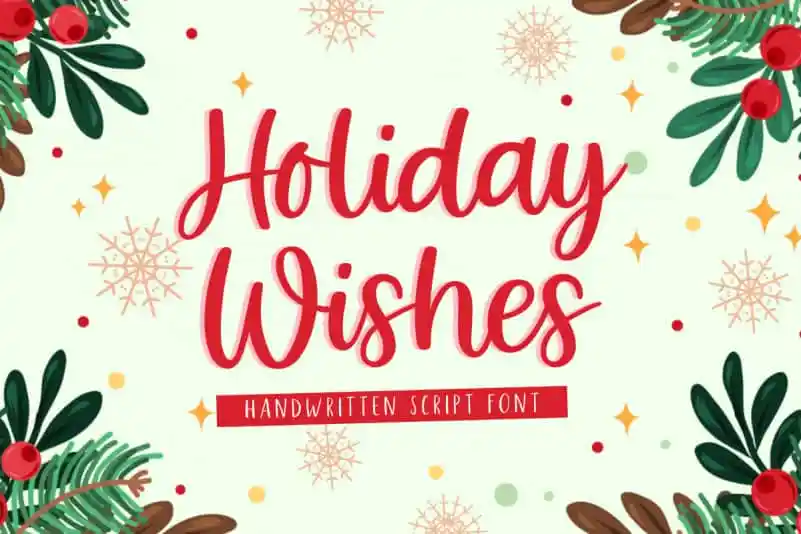
Holiday Wishes Script Font – Fonte Grátis
Holiday Wishes Script Font
A fonte ‘Holiday Wishes Script Font’ é uma elegante tipografia escrita à mão que adicionará um toque fresco e moderno a seus designs digitais. Com seu caráter natural e fluido, esta fonte será perfeita para estilos de branding, design digital, redes sociais, websites, blogs, cartões de business, Instagram, convites, logotipos e até mesmo criações personalizadas no Cricut. Suas linhas suaves e características únicas garantem que sua identidade visual seja única, se destacando em qualquer plataforma ou aplicação digital onde ela for usada. A ‘Holiday Wishes Script Font’ é uma ótima opção para quem busca um design elegante e criativo para seus projetos de fim de ano.